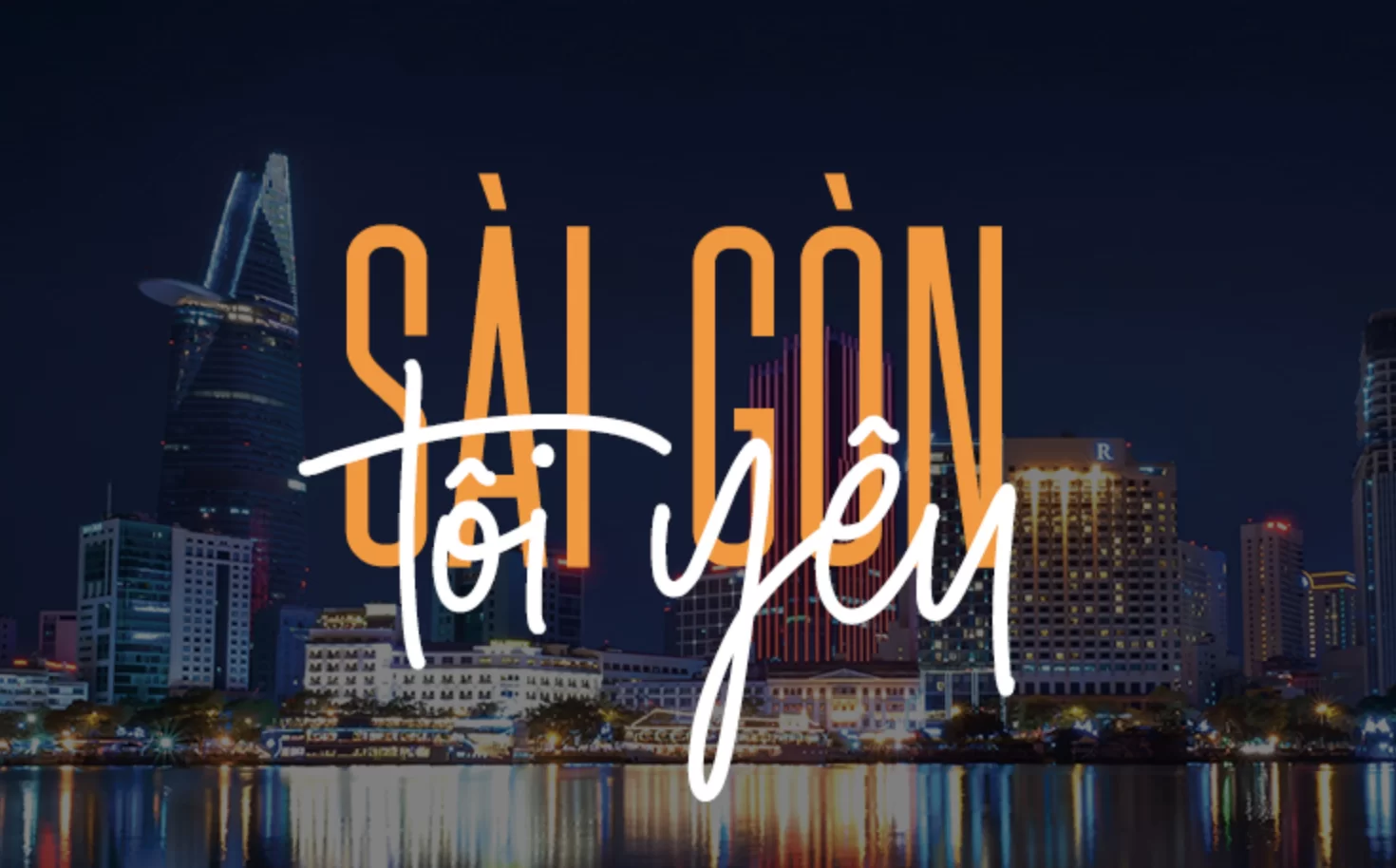
[Font Việt hóa] SVN-Golden Youth
Giới thiệu về Golden Youth Font Duo, một phong cách hiện đại và hài hòa của kiểu chữ sans & chữ viết táy. Với phông chữ sans-serif có vân cao và một người bạn đồng hành tự do, Golden Youth cung cấp kiểu chữ tương phản đẹp cho nhiều dự án thiết kế, bao gồm: biểu trưng & xây dựng thương hiệu, thiết kế bao bì, bài đăng phương tiện truyền thông xã hội, quảng cáo và thiết kế sản phẩm.
Kiểu: Caps & Script